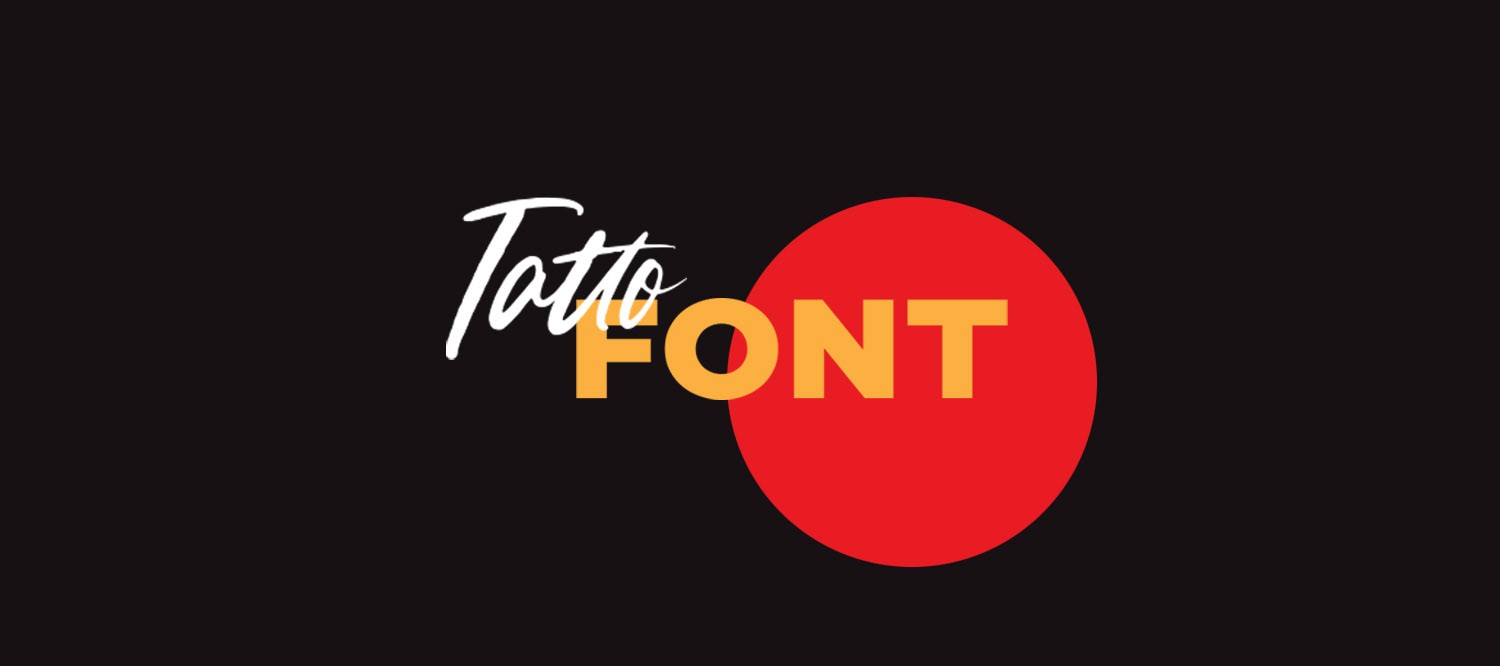
Font chữ tattoo là các kiểu chữ đặc biệt được sử dụng trong thiết kế hình xăm. Chúng không chỉ là chữ viết thông thường mà còn thể hiện cá tính và phong cách của người sở hữu hình xăm. Font chữ tattoo thường mang những đặc điểm nổi bật, từ nét chữ mạnh mẽ, mềm mại đến cổ điển, hiện đại, tạo ra sự khác biệt và ấn tượng cho từng thiết kế.
Việc chọn font chữ phù hợp sẽ ảnh hưởng trực tiếp đến thẩm mỹ và ý nghĩa của hình xăm. Một font chữ đẹp, dễ đọc và phù hợp với chủ đề sẽ giúp hình xăm trở nên sống động và phản ánh đúng cá tính của người sở hữu. Hơn nữa, lựa chọn đúng font giúp hình xăm của bạn dễ nhìn hơn khi thực hiện và không bị “mất hình” sau một thời gian.
Trong những năm gần đây, việc lựa chọn font chữ tattoo đã trở thành một xu hướng phổ biến. Các font chữ độc đáo, dễ nhận diện và mang đậm dấu ấn cá nhân được ưa chuộng, thay thế cho những hình xăm truyền thống. Điều này không chỉ là sự đổi mới trong nghệ thuật xăm mà còn giúp người xăm thể hiện bản thân một cách rõ ràng và nổi bật.
Font chữ Việt hóa về lịch sử Nhật Bản
Font chữ này mang đậm ảnh hưởng của văn hóa Nhật Bản, với những nét chữ mềm mại, dễ đọc, rất phù hợp cho các thiết kế hình xăm mang đậm tính lịch sử và truyền thống.
Font chữ Việt hóa phong cách vintage
Với những đường nét uốn lượn nhẹ nhàng và cổ điển, font chữ này rất thích hợp cho các thiết kế mang đậm dấu ấn thời gian và sự hoài niệm.
Font chữ Việt hóa phong cách calligraphy Chicanos
Một font chữ mang đậm chất thư pháp, với các nét chữ sắc sảo và mềm mại, rất phù hợp cho những ai yêu thích sự uyển chuyển và nghệ thuật xăm hình.
Font chữ vintage Việt hóa – Bistern
Font chữ này mang phong cách cổ điển, có sự kết hợp giữa nét vẽ tay và sự mạnh mẽ, tạo nên một phong cách vintage độc đáo cho hình xăm.
Font chữ Spa Việt hóa - Waking cho phong cách hiện đại luxury
Một font chữ mang đậm phong cách hiện đại, thanh thoát, với những đường nét tinh tế và sang trọng, rất thích hợp cho các thiết kế xăm tối giản.
Phông chữ phong cách hiện đại và sang trọng - Luxury
Đây là font chữ với sự kết hợp hoàn hảo giữa sự hiện đại và sang trọng, phù hợp cho những hình xăm mang đậm phong cách quý phái.
7. Font chữ hiện đại cho lĩnh vực thể thao Việt hóa - Futurama
Font chữ này có thiết kế sắc nét, mạnh mẽ, mang đậm tính thể thao, rất thích hợp cho những ai muốn thể hiện cá tính năng động và mạnh mẽ qua hình xăm.
Font chữ game đối kháng mạnh mẽ Việt hóa - Cungcap 10
Được lấy cảm hứng từ các trò chơi điện tử, font chữ này mang lại sự mạnh mẽ, táo bạo, phù hợp với những thiết kế hình xăm dành cho game thủ và những người yêu thích sự cá tính mạnh mẽ.
Font chữ chữ đê lịch sử Việt hóa
Một font chữ mang đậm dấu ấn lịch sử, phù hợp với các thiết kế xăm mang ý nghĩa tâm linh, văn hóa. Với các nét chữ mạnh mẽ, cổ điển, font này mang lại sự trang nghiêm và uy nghiêm.
Font chữ kiểu Thái Lan Việt hóa - Sawadikap
Với phong cách độc đáo, font chữ này mang đậm nét văn hóa Thái Lan, tạo nên những thiết kế xăm đẹp mắt và lạ mắt, phù hợp cho những ai yêu thích văn hóa châu Á.
Font chữ cổ trang Việt hóa - Zahra cho thiết kế đồ họa
Font chữ này mang phong cách cổ trang, rất phù hợp cho những thiết kế xăm đậm chất huyền bí và nghệ thuật. Được yêu thích trong các thiết kế có yếu tố văn hóa.
Font chữ ký Việt tay - Boulderstone Việt hóa
Đây là một font chữ viết tay với nét chữ đậm và mảnh, tạo sự ấn tượng mạnh mẽ. Font này rất phù hợp cho những ai yêu thích các hình xăm có chữ ký hoặc thông điệp cá nhân.
Font chữ có chân serif - Marlino Regular Việt hóa
Một font chữ kiểu serif, mang lại sự sang trọng và tinh tế, thích hợp cho những hình xăm có thông điệp sâu sắc và mang tính chất nghiêm túc.
Font chữ thanh lịch cho thiệp cưới - Griffiths Việt hóa
Font chữ này có thiết kế thanh lịch, rất thích hợp cho những hình xăm mang tính chất trang trọng và thanh nhã, đặc biệt là các thông điệp trong đám cưới hoặc kỷ niệm.
Font chữ FZ Thư pháp bút bi
Font chữ này mang đậm tính thư pháp, với những nét chữ uốn lượn mềm mại, phù hợp cho những hình xăm nghệ thuật và tinh tế.
Độ dễ đọc và thẩm mỹ
Lựa chọn font chữ tattoo cần đảm bảo rằng chữ sẽ dễ đọc và không bị nhòe hoặc mất hình sau một thời gian. Điều này đặc biệt quan trọng khi xăm chữ vào những vị trí nhỏ hoặc chi tiết như ngón tay, cổ tay, hoặc cổ.
Phù hợp với phong cách và ý nghĩa hình xăm
Mỗi hình xăm đều mang một thông điệp riêng, vì vậy font chữ phải phù hợp với ý nghĩa mà người xăm muốn thể hiện. Ví dụ, một hình xăm mang tính tôn giáo sẽ cần một font chữ cổ điển, trang nghiêm, trong khi một hình xăm thể hiện sự tự do có thể chọn những font chữ mềm mại, bay bổng.
Font chữ tattoo không chỉ là yếu tố thẩm mỹ, mà còn ảnh hưởng đến ý nghĩa của hình xăm. Việc chọn lựa font chữ phù hợp giúp hình xăm trở nên đẹp mắt và có ý nghĩa hơn. Hãy thử nghiệm nhiều font khác nhau và đừng quên tham khảo ý kiến của những người có kinh nghiệm hoặc chuyên gia xăm để có lựa chọn tốt nhất cho thiết kế của mình